因为网络在不断发展,所以电脑设计字体也受到很多人的关注。很多人认为字体设计很简单,但其实字体设计中隐藏了很多小技巧,如果不细心的话,很难发现这些隐藏的技巧。字体设计并不是简单的字体类型设计,而是一种语言与视觉形式的结合,也可以说字体设计就是平面设计。在设计字体时,不仅仅要设计字体的类型,更要把文字进行图文化。那么大家知道怎么进行字体设计吗?下面将为大家介绍怎么设计字体的相关内容。
一、替换法
怎么设计字体?替换法是常用的。替换法就是在同一类型的文字中加入一些创意或者是一些另类的字体,将它们进行融合,就可以设计出一种新的字体。也可以用某一形象或者某一图画来代替字体的笔画,这种方法也是经常被使用的。
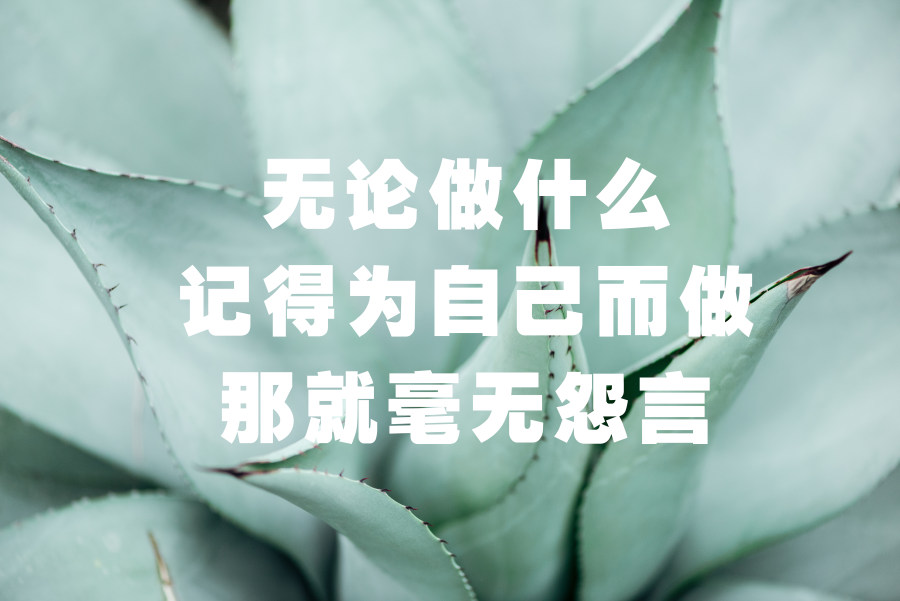
二、叠加法
对于喜欢设计字体的人来说,叠加法应该是设计字体最常用的一种方法。叠加法有三种形式,第一种形式是将这个笔画进行叠加,第二种形式是将字与字进行介绍,第三种形式则是教字与笔画进行叠加,第三种形式是最常用的,大家在设计字体是可以尝试一下第三种形式。
三、俏皮设计法
俏皮设计法是需要创意的,很多年轻人都喜欢用这种方法来设计字体。可以改变字体的笔画或者是改变字体的笔触,例如用圆弧来代替角,这种设计字体的方法是比较简单的。
以上就是为大家介绍的关于怎么设计字体的具体方法,以上这三种方法都是比较常用的,大家在设计字体是可以尝试一下。